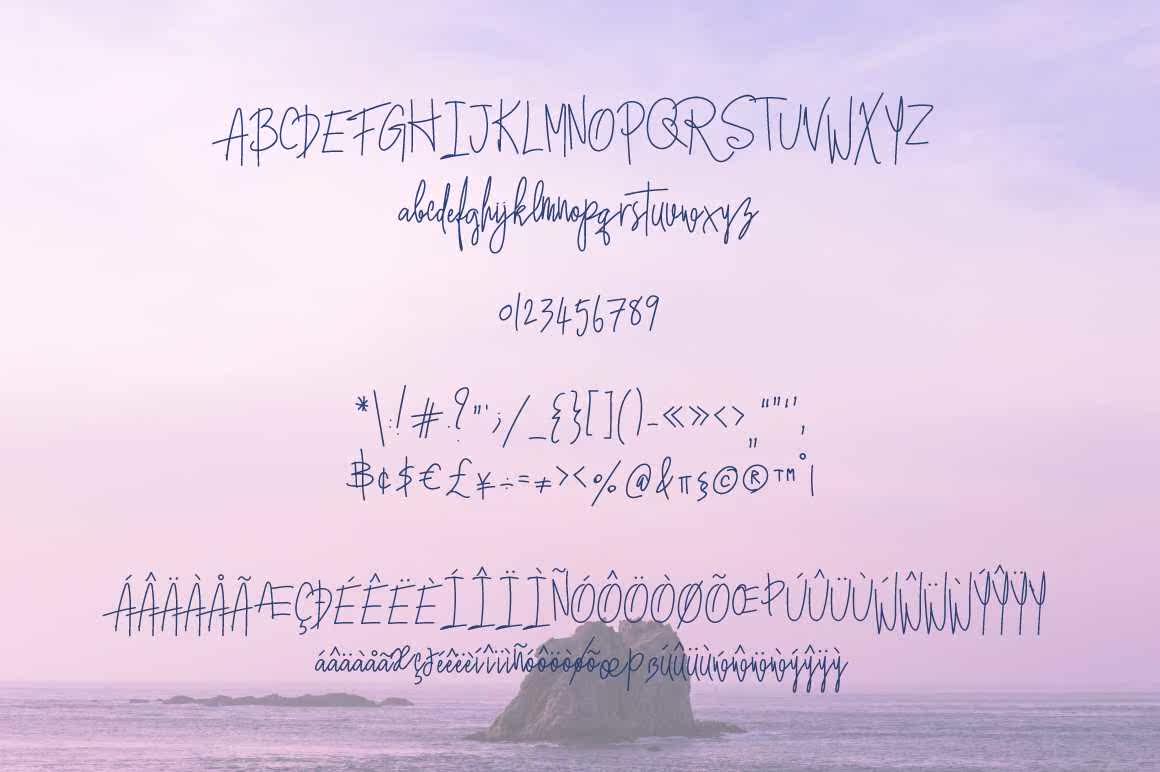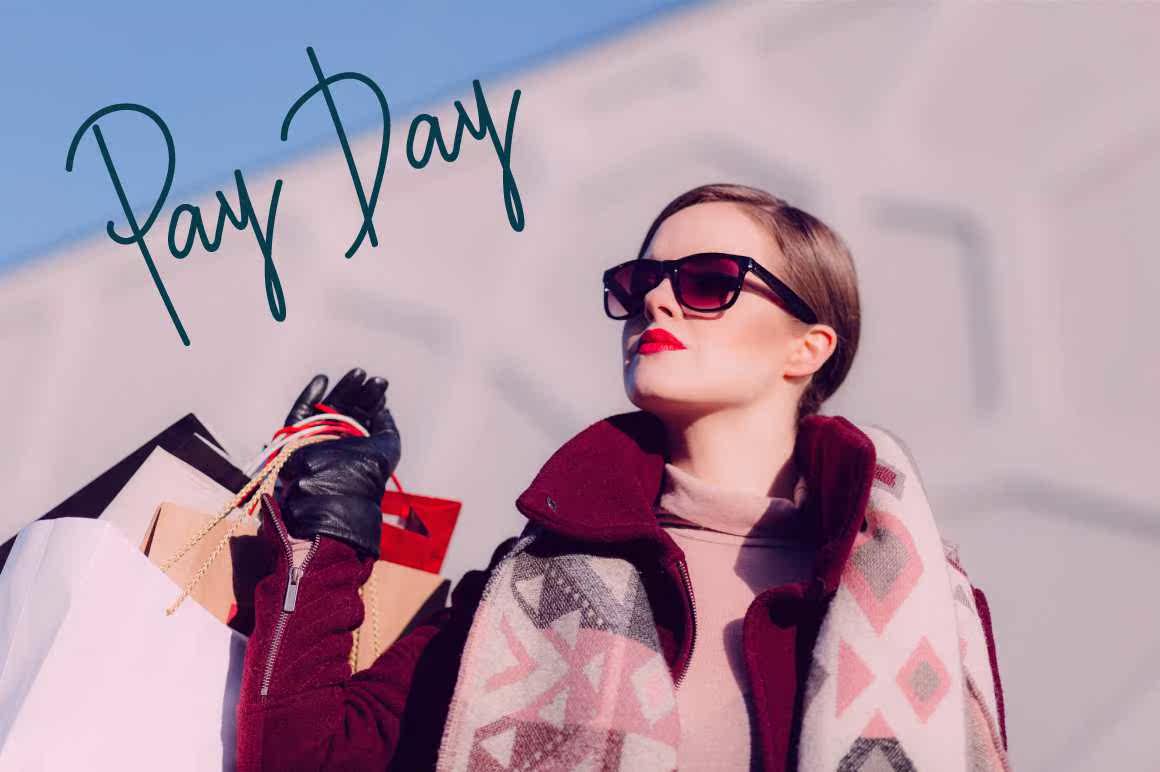
ArduIniSah和Writing手写体字体设计为TogiveOffaboutingandClassyVibe。Arduin是指一位好友。它是一种手写体,但仍然可读。它可以用于为您的品牌项目、企业身份、标签、贴纸、包装设计、装置设计、,Arduin和Writing手写字体设计为TogiveOffabouncing和ClassyVibe。Arduin是指一位好友。它是一种手写字体,但仍然可读。它可以用于为您的品牌项目、公司身份、标签、贴纸、包装设计、装置标志等创建一个现代非谷歌设计。